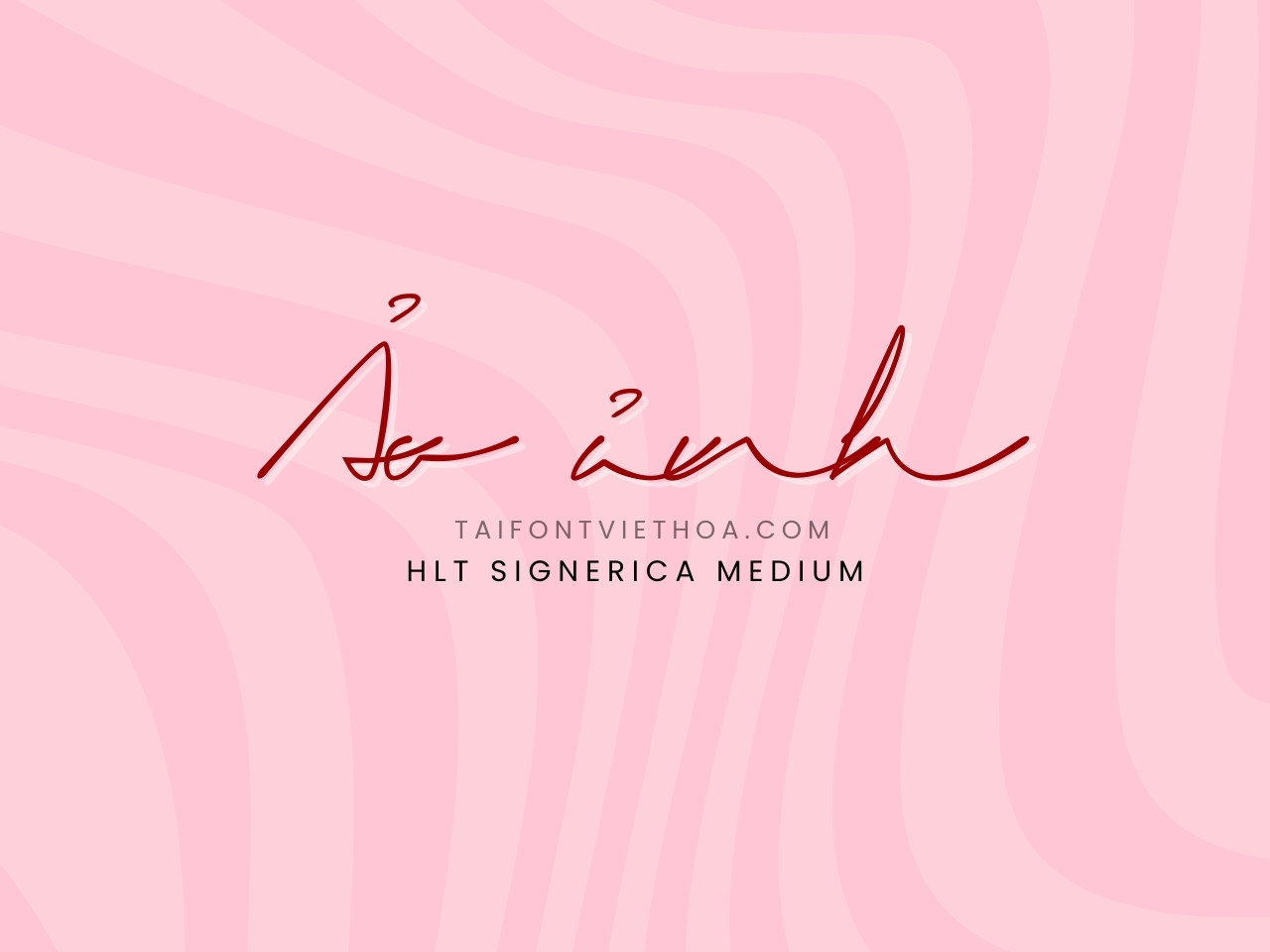
Font việt hóa HLT Signerica Medium
HLT Signerica Medium – Font chữ ký mềm mại và thanh lịch
HLT Signerica Medium là phiên bản Việt hóa từ font gốc “Signerica Medium” – một font chữ mang phong cách chữ ký (signature) đặc trưng, do Mårten Forth công bố thông qua MRF Fonts. Font này lần đầu xuất hiện trên các nền tảng chia sẻ font quốc tế từ những năm 2010, và nhanh chóng trở thành lựa chọn phổ biến cho các thiết kế mang tính cá nhân hóa cao. Signerica Medium hỗ trợ hơn 50 ngôn ngữ dựa trên bảng chữ cái Latinh, đặc biệt phù hợp với các thiết kế tinh tế, mang hơi hướng thủ công.
Phiên bản Việt hóa được thực hiện bởi nhóm HLT Fonts, đảm bảo sự tương thích hoàn toàn với tiếng Việt có dấu, đồng thời giữ nguyên tính thẩm mỹ mượt mà của bản gốc. Từng ký tự được cân chỉnh tỉ mỉ nhằm tạo cảm giác như được viết tay thực sự. Font đã được taifontviethoa.com sưu tầm, chọn lọc và kiểm tra thực tế qua nhiều dự án thiết kế. Việc chia sẻ font này nhằm đáp ứng nhu cầu sử dụng font chữ ký trong thiết kế logo, thiệp cưới, và các ứng dụng branding mang tính nghệ thuật cao tại Việt Nam.
Đặc điểm thiết kế và ứng dụng nổi bật của HLT Signerica Medium
Signerica Medium sở hữu các nét chữ mảnh, độ cong uyển chuyển, kết nối tự nhiên như một dòng chảy liên tục. Các ký tự có độ nghiêng vừa phải, tạo cảm giác mềm mại và nhẹ nhàng, lý tưởng cho các thiết kế yêu cầu sự tinh tế, thân thiện. Đây là một kiểu font script theo dạng handwritten nhưng được thiết kế tối ưu để dễ đọc và dễ ứng dụng trên nhiều nền tảng.
Font phù hợp với nhiều lĩnh vực như thiết kế logo cá nhân, thiệp mời, tiêu đề blog, bài đăng trên mạng xã hội hoặc các chiến dịch marketing yêu cầu chất thơ, tính nghệ thuật và phong cách nữ tính. Đặc biệt, các thương hiệu trong lĩnh vực spa, thời trang cao cấp, mỹ phẩm hoặc wedding planner thường ưu ái sử dụng font chữ ký như Signerica để làm nổi bật tính cá nhân hóa và cảm xúc trong thiết kế.